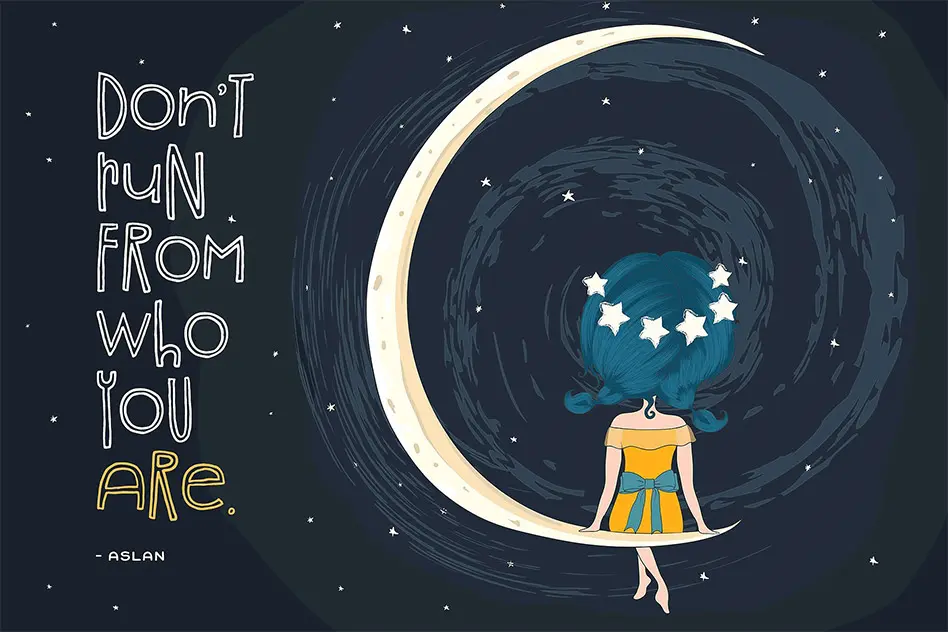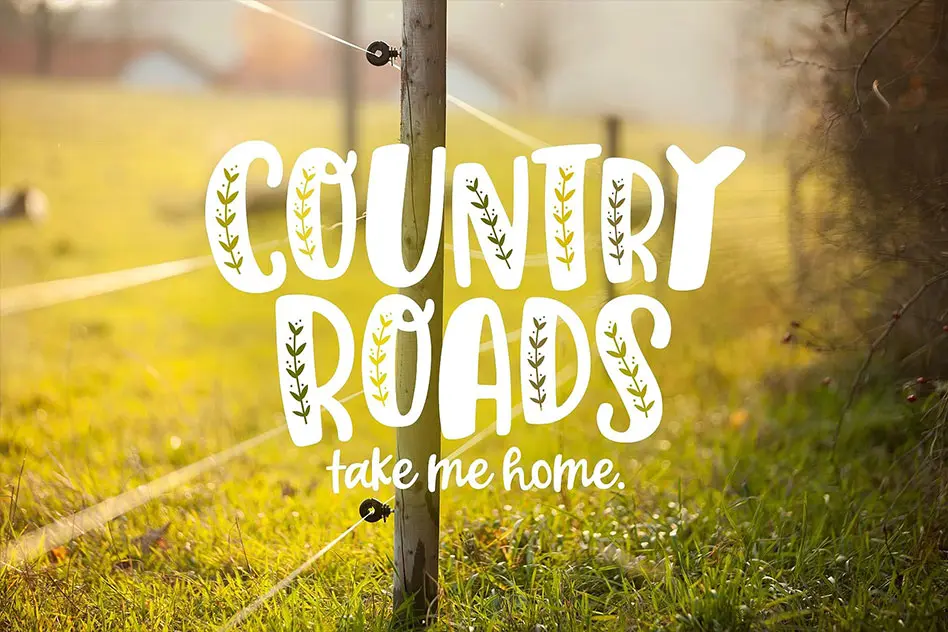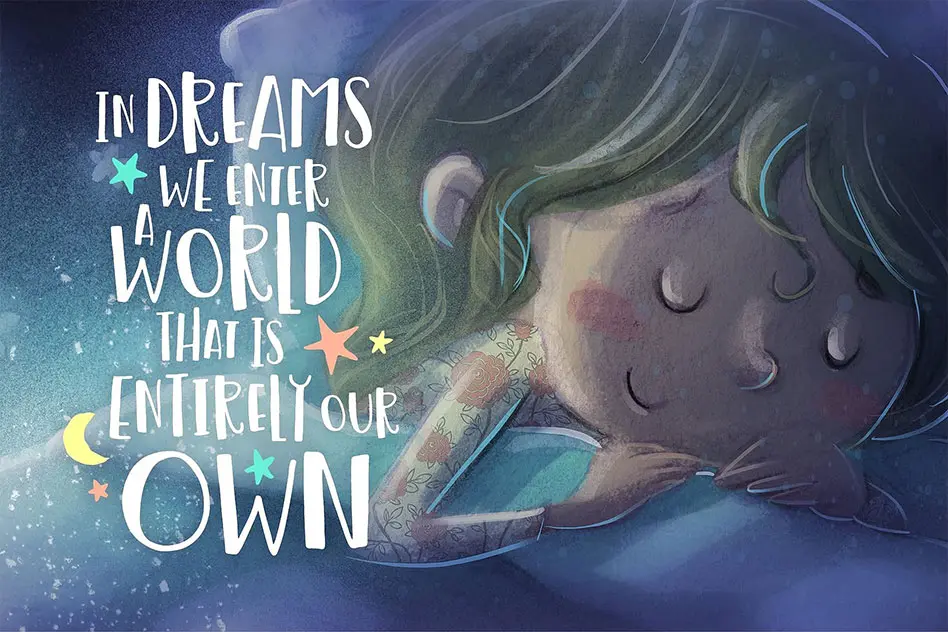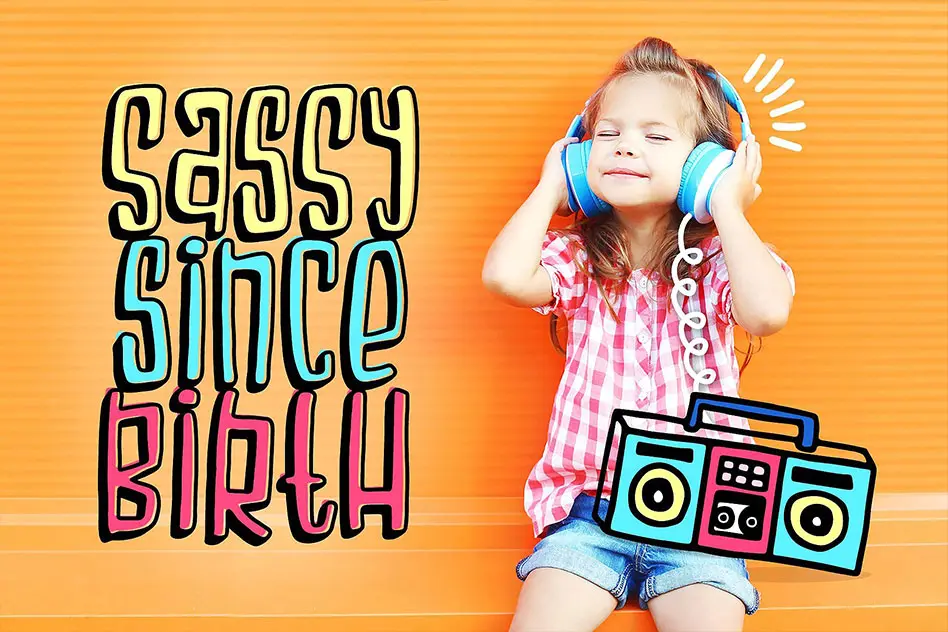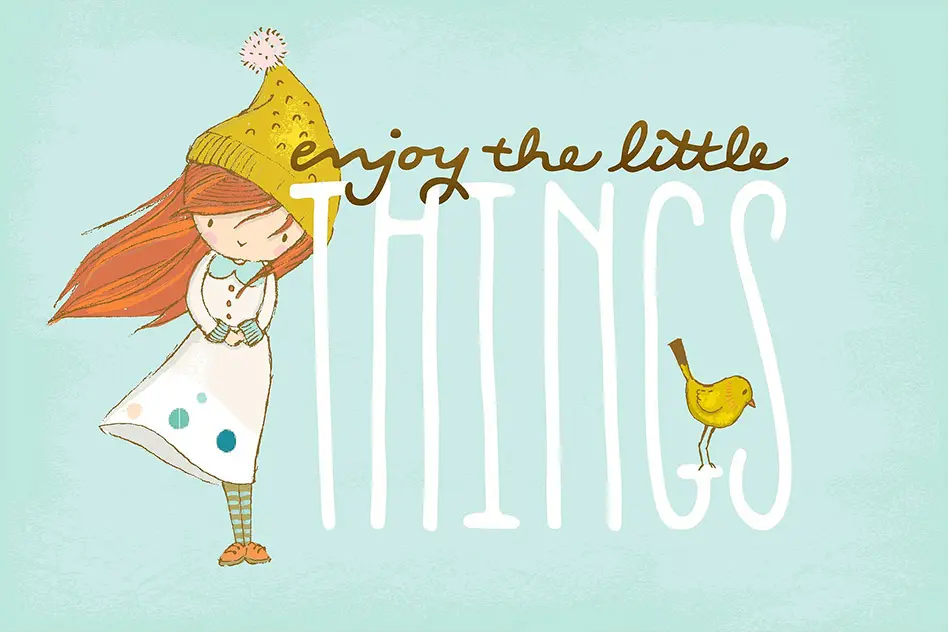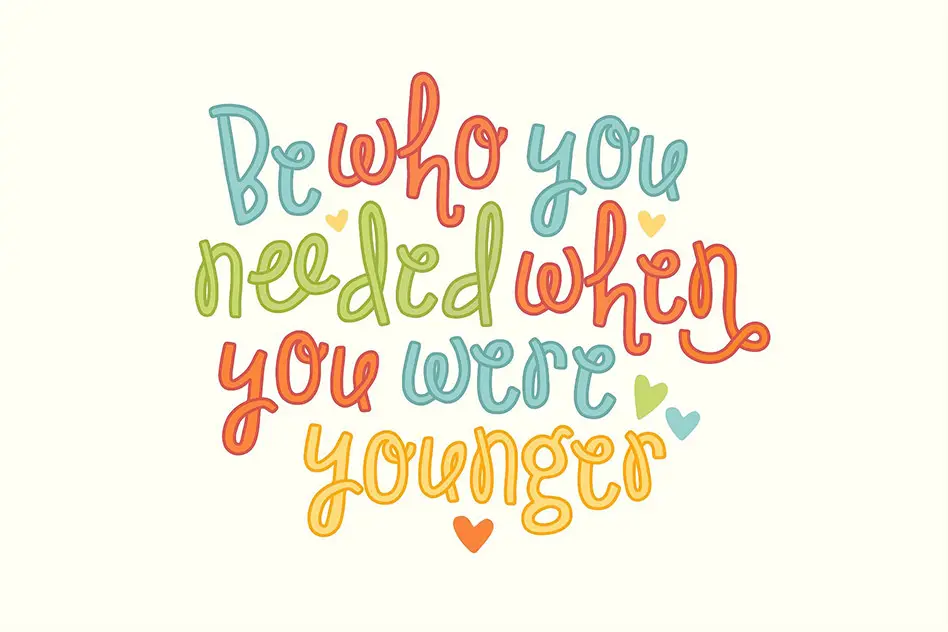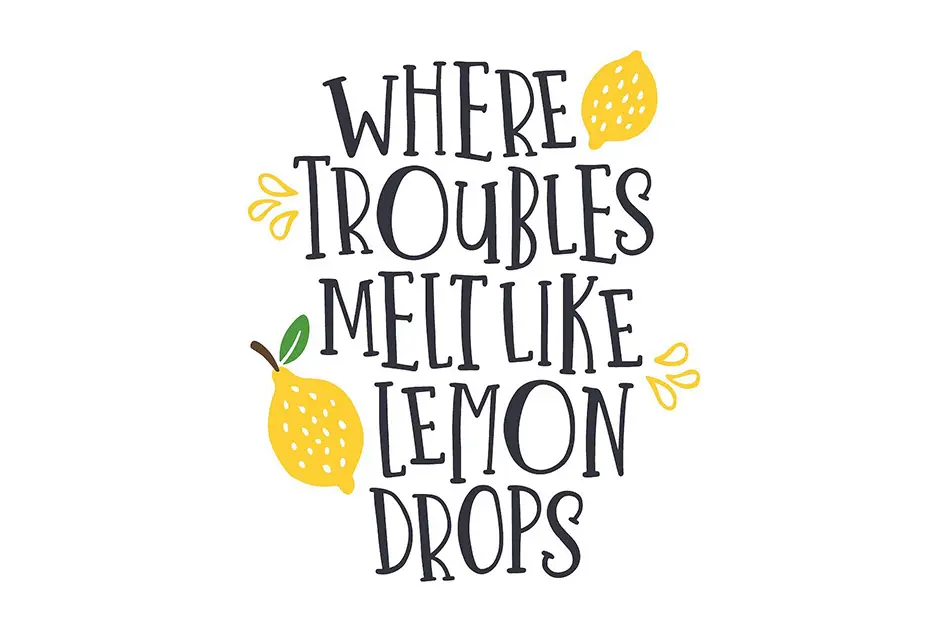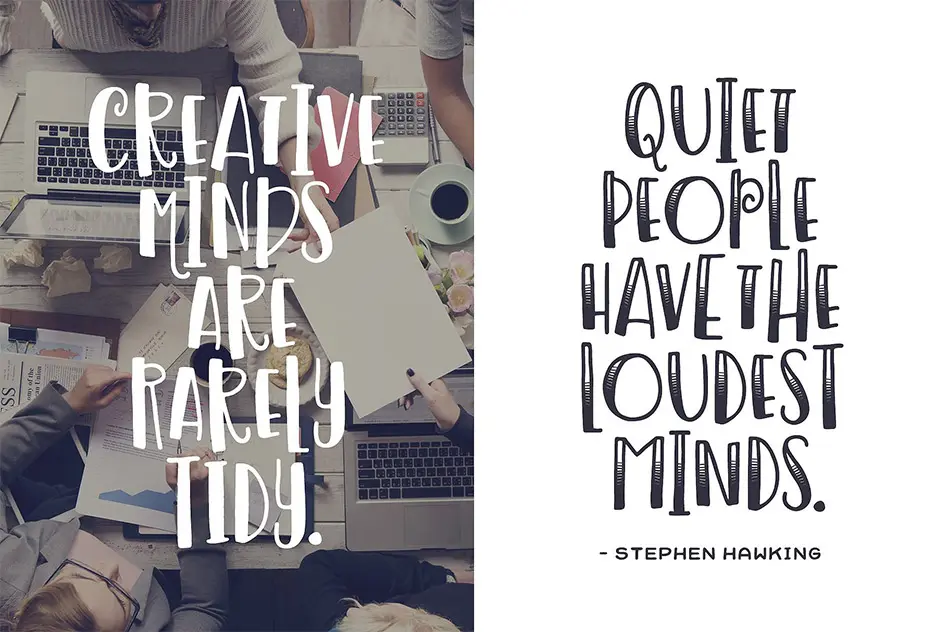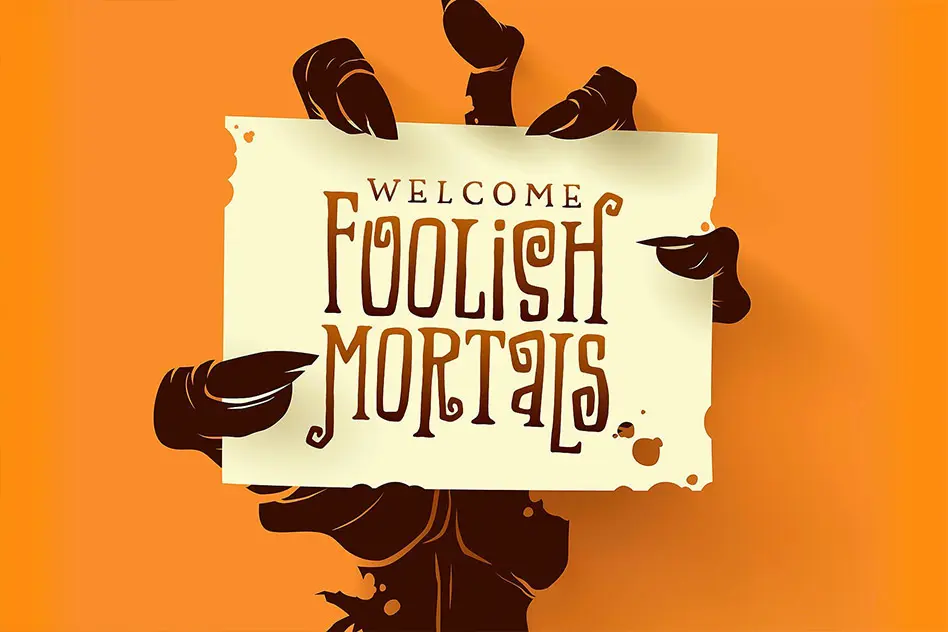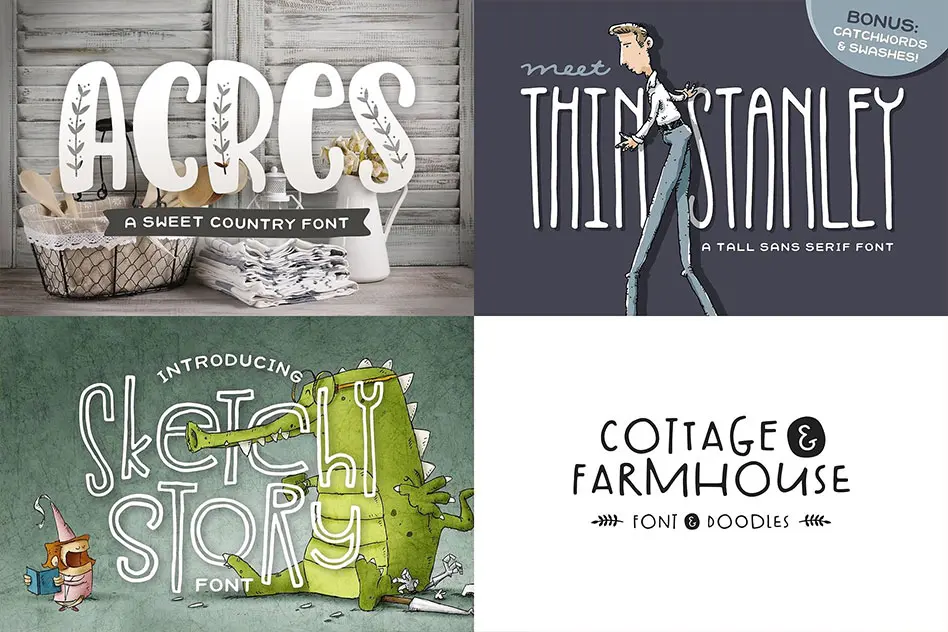
در این پست شاهد مجموعه 12 فونت انگلیسی فانتزی و کودکانه فوق العاده زیبا با نام Sweet Dreams مناسب جهت ایجاد طرح های فانتزی و کودکانه می باشید. این مجموعه فونت زیبا در قالب فایل های ttf و otf در سایت بارگذاری شده اند که با نصب یکی از این دو فرمت در پوشه فونت های سیستم قادر به استفاده از آن ها در تمام نرم افزارهای گرافیکی و ویرایشگر متن از جمله نرم افزار محبوب فتوشاپ ، ایلاستریتور ، افترافکت ، پریمیر ، مجموعه نرم افزار آفیس و … خواهید بود. مجموعه فونت Sweet Dreams شامل 12 فونت از خانواده فونت های فانتزی و کودکانه است که در وزن های مختلف طراحی شده اند و شما بسته به نیاز و سلیقه خود می توانید از هر کدام در طرح های خود استفاده نمائید. همچنین کلیه عناصر تزئینی این مجموعه فونت هم به صورت وکتور در قالب فایل های eps و ai و هم به صورت فونت های سمبل در فایل فشرده موجود بوده که از آن ها نیز می توانید در پروژه های خود بهره مند گردید.
موارد استفاده مجموعه فونت Sweet Dreams
از این مجموعه فونت می توان در ایجاد طرح های فانتزی و کودکانه همچون انواع کارت تبریک ، کارت پستال ، قاب عکس ، طراحی بر روی پارچه و لباس ، طراحی انواع پوستر ، چاپ بر روی ظروف سلولزی ، طراحی کارت ویزیت ، چاپ بر روی انواع کیف و ساک دستی ، طراحی بر روی انواع دکورهای تزئینی ، طراحی انواع لوگو و صدها مورد دیگر استفاده نمود.